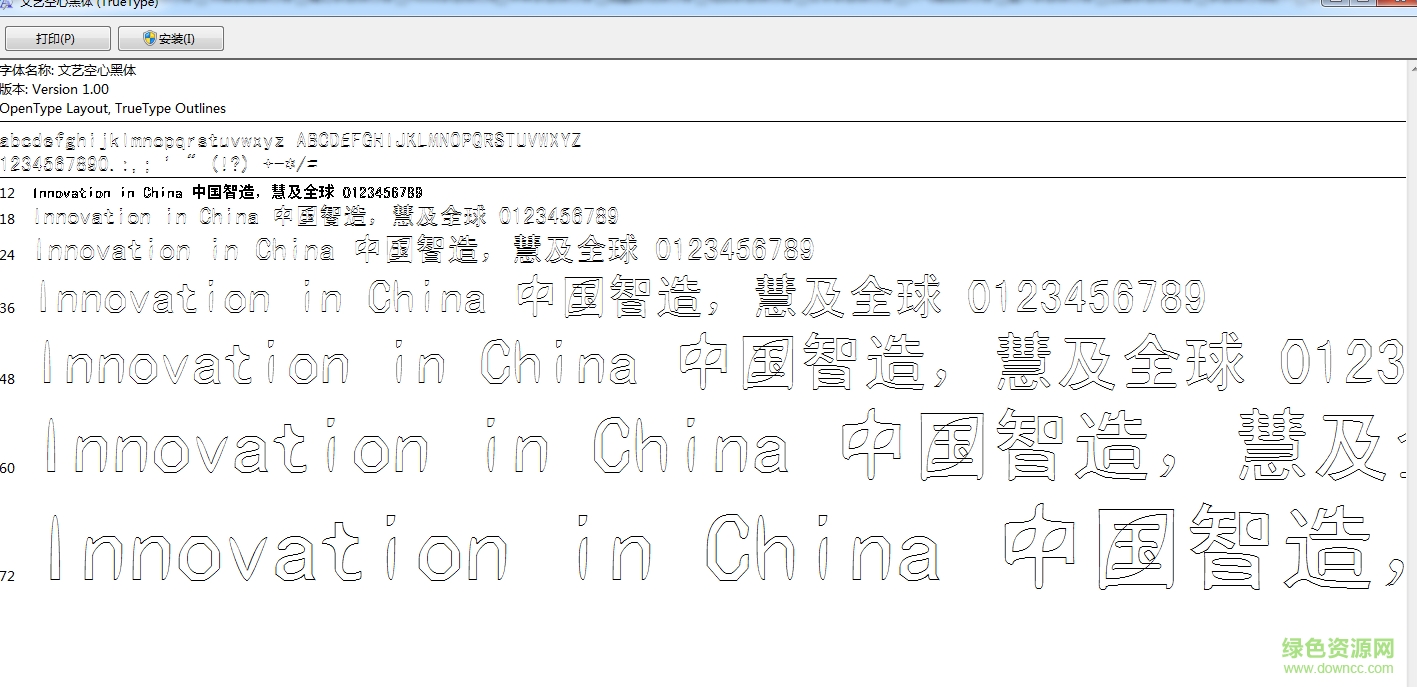
文藝空心黑體字體
文藝空心黑體是一款風格獨特的藝術(shù)字體,暗黑味十足,筆畫犀利,棱角分明,美觀而不落俗套,常用于各種藝術(shù)創(chuàng)作!喜歡的朋友趕緊來綠色資源網(wǎng)下載喲!
文藝空心黑體字體風格非常獨特,筆畫輕盈,點畫精致,轉(zhuǎn)折十分舒展嗎,常常用于各類海報、雜志、書刊或廣告中!